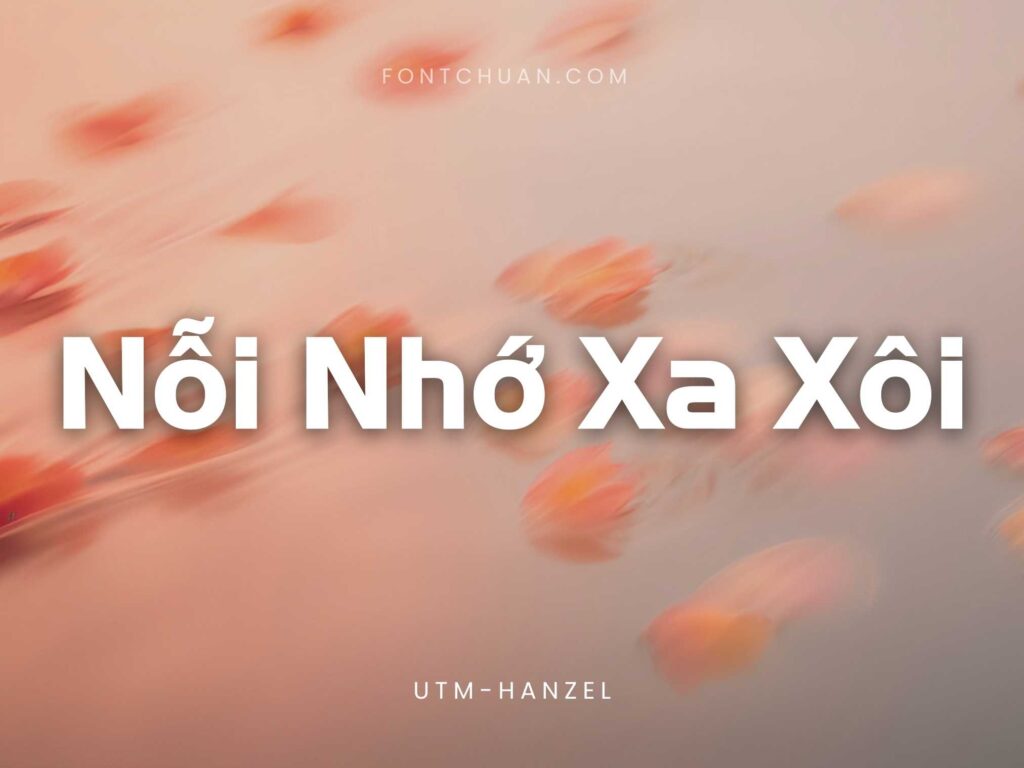
UTM Hanzel là một font chữ sáng tạo mang phong cách hiện đại và mạnh mẽ, phù hợp với nhiều thiết kế đòi hỏi sự nổi bật và cá tính. Font này có sự kết hợp giữa đường nét cứng cáp và độ cong mềm mại, tạo nên một diện mạo chuyên nghiệp và đầy ấn tượng. Font đã được Việt hóa bởi Thiên Minh, hỗ trợ đầy đủ tiếng Việt cùng hơn 200 ngôn ngữ khác, giúp mở rộng khả năng ứng dụng. Thành viên của Font Chuẩn đã sưu tầm và giới thiệu font này nhằm đáp ứng nhu cầu bạn đọc, cung cấp nguồn tham khảo chất lượng và ứng dụng thực tế vào các dự án thiết kế
Về đặc điểm thiết kế, UTM Hanzel có cấu trúc chữ táo bạo, độ dày đồng đều và cảm giác hiện đại. Font này phù hợp với các ứng dụng như thiết kế thương hiệu, tiêu đề lớn, poster, biển hiệu và bao bì sản phẩm. Các ngành nghề như công nghệ, quảng cáo, giáo dục và thiết kế thương hiệu có thể tận dụng font này để tạo điểm nhấn và tăng tính chuyên nghiệp trong các sản phẩm thiết kế